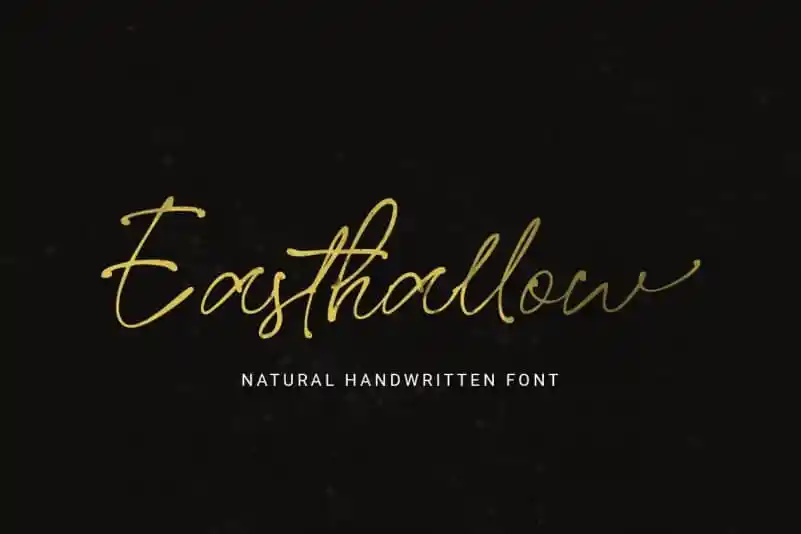
Easthallow Handwritten Font – Download Grátis
Easthallow é uma elegante fonte escrita a mão que traz um toque natural e feminino aos seus projetos. Fundamentada na tipografia de assinatura sofisticada, esta font oferece curvas únicas e um fluxo fluido, como se fosse esculpida à mão. Desenvolvida pelo designer Rillatype, Easthallow é perfeita para criar logos de assinaturas, convites de casamento, marcações e mais. Com seu charme elegante e estilo inconfundível, esta font vai tornar seus projetos ainda mais únicos e atraentes. Experimente Easthallow na sua próxima criação gráfica e dê um toque especial à sua identidade visual.